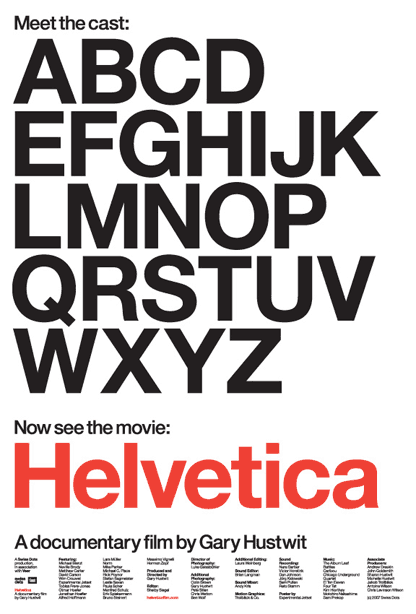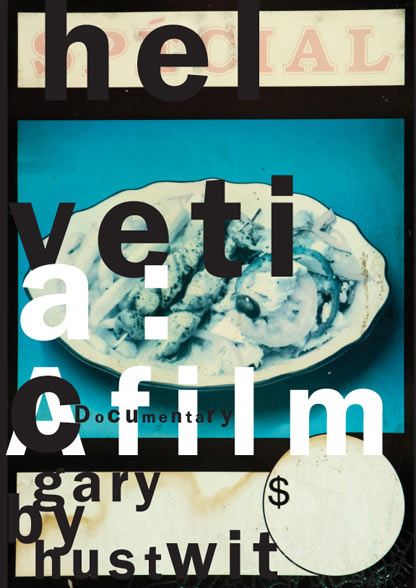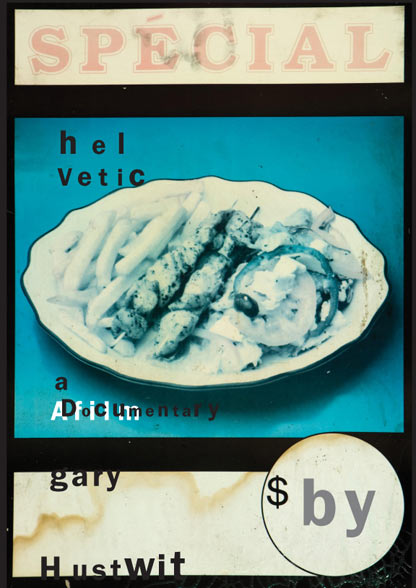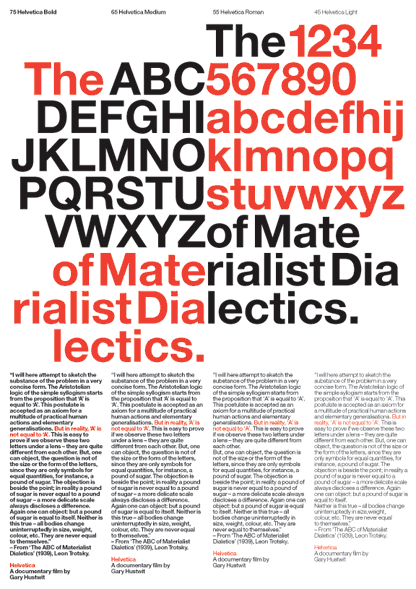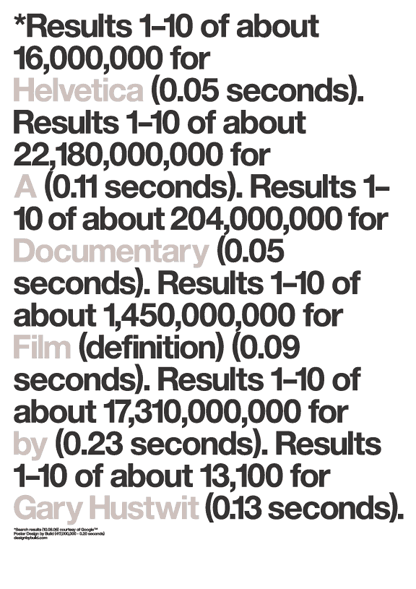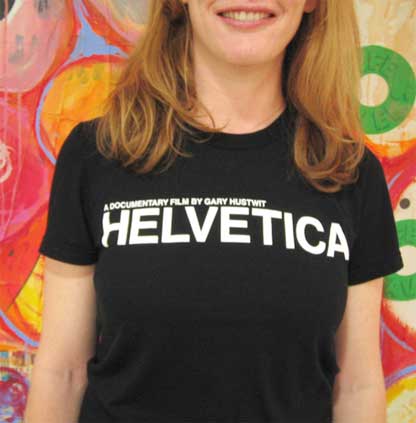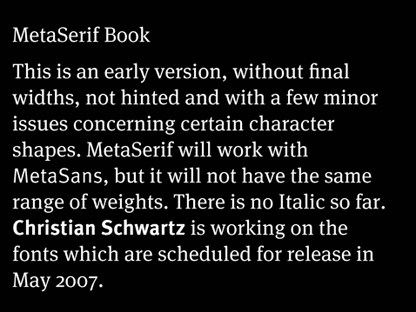
Erik Spiekermann launch MetaSerif Book, during the year of Helvetica | visionnaire ou provocateur?
Vous connaissez tous le créateur de FontShop, MetaDesign, celui qui dessina l’Officina, le Berliner, le LoType, et surtout le Meta (en 1989)… C’est un des plus brillants typographes créateur et en même temps stratège-marketing dans le monde *sans pitié* des nouvelles fonderies indépendantes numériques. C’est celui qui convainct Neville Brody de participer à l’aventure de Fuse et de Font-Font, les FF qui deviendront aussi célèbres que la Créative Alliance ou les caractères Emigre ou plus simplement les ITC.
Il vient d’annoncer sur son blog le prochain achèvement d’un programme de création, la MetaSerif Book. Ce serait une anecdote de plus, si la date choisie ne correspondait pas précisément au lancement en Europe du Film de Gary Hustwit concernant l’hommage unanime de la planète, à l’inventeur de l’Helvetica: Max Miedinger. Il y a chez Erik Spiekermann un certain sens du spectacle. Il a toujours aimé faire le clown et se faire s’écrouler de rire la galerie des professionnels qui se réunissent chaque année pour les conférences de l’Atypi (Association Typographique Internationale). Et je trouve pour ma part que la sortie du MetaSerif Book est l’une de ses belles farces mi-figue mi-bas de casse qui a le don d’agacer plus d’un dans la communauté typographique. Car enfin, de quoi s’agit-il?•••••
Hermann Zapf, Paula Scher, Experimental JetSet, Neville Brody, Wim Crouwel, Mattew Carter, et bien sûr, Erik Spiekermann sans les citer tous, ont participé à ce documentaire majeur qui va célébrer la naissance et la domination de cette typo tout au long du vingtième siècle, débordant largement sur le XXIe, puisque les plus grandes marques comme Apple, BMW, Orange etc. continuent de s’en servir pour leur branding. Nous sommes ici avec l’Helvetica à l’opposé de la démarche de M6 qui viennent d’abandonner l’habillage de Robial. Hélas. L’Helvetica ? on a tout dit. Qu’il est beau, je dirai remarquablement bien dessiné. Qu’il est neutre. Comme si un caractère, sous l’angle antropomorphique pouvait prétendre à la moindre neutralité… autant dire que le visage de Tom Cruise est neutre au prétexte qu’il n’a pris aucune ride ;-)
Quelques affiches et matériels *dérivés* pour la promotion du film.
Réalisation: David Carson, pas très à l’aise dans un registre où la typo seule tient la vedette. On est loin de ses plus belles créations. Il nous avait habitué à un travail de plasticien beaucoup plus *intégré*. C’est à peine qu’il se permet quelques superpositions mal à propos. Qu’importe, il en est. De la fête.
Le teeshirt officiel du film.
•••••• Mais revenons à Erik Spiekermann et à son MetaSerif Book. Un Georgia qui ne dit son nom, une Transitionnelle-Réale bien engraissée, légèrement germanisante à la manière des caractères d’Hermann Zapf et de Poppl il démontre une fois de plus que la culture environnante est terriblement pregnante. Mais il nous parle surtout d’autre chose. Spiekermann comme beaucoup d’entre-nous sait très bien que l’Helvetica en est à son apogée cette année. La mode va passer. Comme toujours, les hommes vont oublier ce qu’ils ont adulé. Trop jeune? vous ne pouvez vous souvenir d’une époque où l’on jeta pour la première fois l’Helvetica pour… redécouvrir le Futura de Paul Renner, ou les News Gothic ou encore les Franklin et bien sûr le Times New Roman. Spiekermann en nous assénant son *Times* personnel, nous en apprend beaucoup sur son sens du commerce et le peu de cas qu’il fait des modes.
Ce n’est pas pour rien qu’il a été à la tête de Font Shop pendant une dizaine d’années. Il connaît tous les chiffres, de la vente en masse des polices dans le monde. Pays par pays. Continent par continent. Ce lancement selon moi est la plus belle pirouette qu’il n’ait jamais faite au moment même où certains naïfs sont persuadés, tels Wim Crouwel, que désormais l’Helvetica va supplanter tous les autres caractères. Bravo Erik. J’en attendais pas moins de ton intelligence supérieure et de ta perspicacité. Alors juste une petite faveur et une remarque, si tu me permets. Perso j’aime beaucoup le MetaSerif Book. S’il te plait, envoie le moi dès qu’il est sorti pour que je puisse le tester pour les lecteurs de *design et typo*. Et puis attention aux Noirs aux Blancs… j’ai déjà proposé récemment une étude sur la lisibilité des caractères sur fond noir. En les teintant légèrement on leur redonne un sacré confort de lecture ;-D